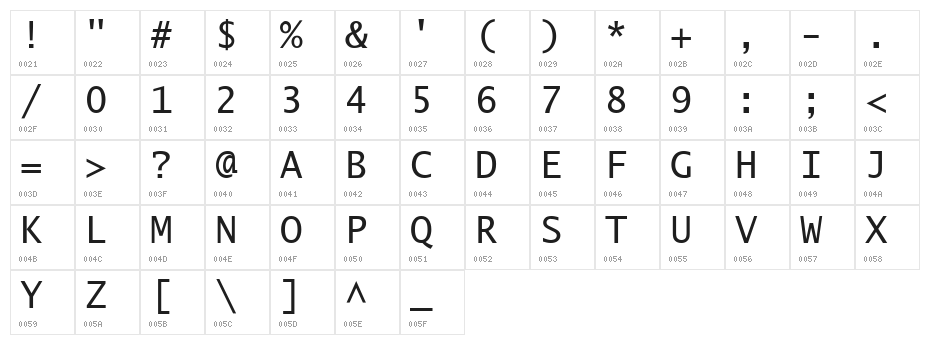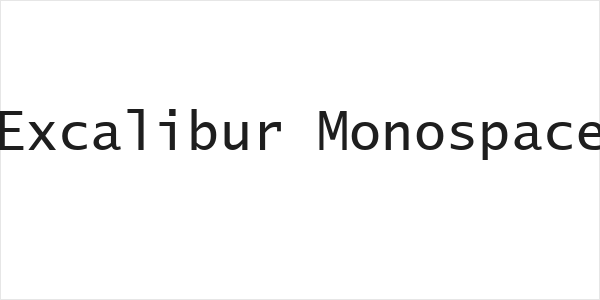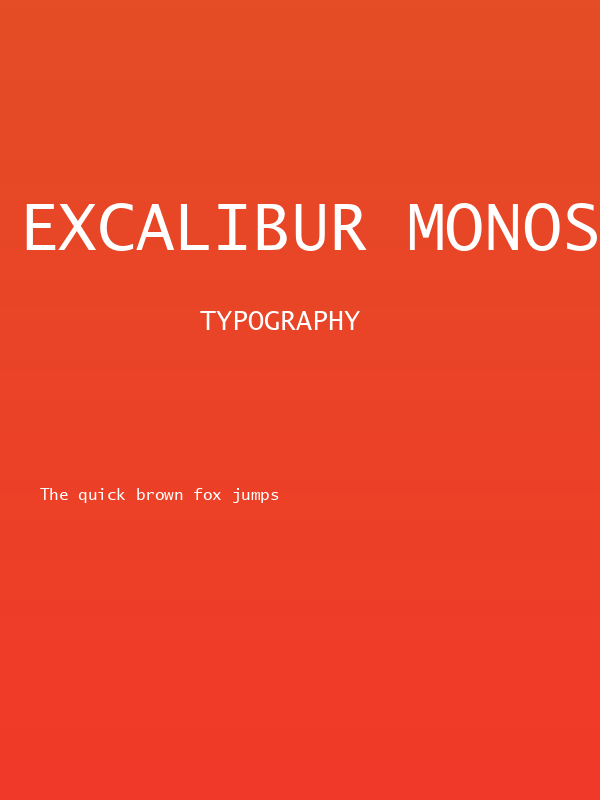
Excalibur Monospace Font
| Caso d'uso | Coding, Technical documentation, Data tables |
| Progetti proposti | Ideal for coding environments, technical documentation, data tables, and any project requiring precise alignment. |